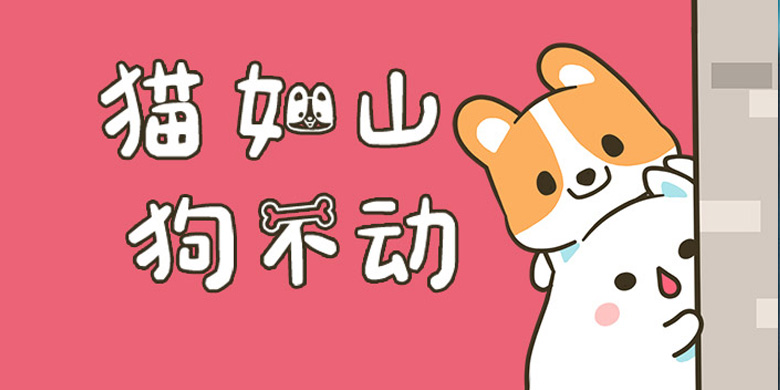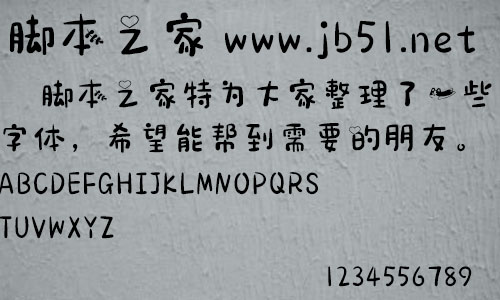
方正手跡-貓如山和狗不動由方正字庫劉曄設(shè)計師出品的藝術(shù)字體,該字粗細變化較大,筆畫簡單直接,結(jié)構(gòu)變化多端,有趣中帶著一下堅實和可愛,適合應(yīng)用于藝術(shù)設(shè)計、平面宣傳設(shè)計、網(wǎng)頁設(shè)計,書法等領(lǐng)域。
這款字粗細變化較大,筆畫簡單直接,結(jié)構(gòu)變化多端,有趣中帶著一下堅實和可愛。還添加了骨頭、愛心、貓咪等掛件元素,顯得更加生動活潑。適用于少年兒童類的書刊、品牌廣告和產(chǎn)品包裝設(shè)計,以及社交網(wǎng)絡(luò)的個性化用字。。